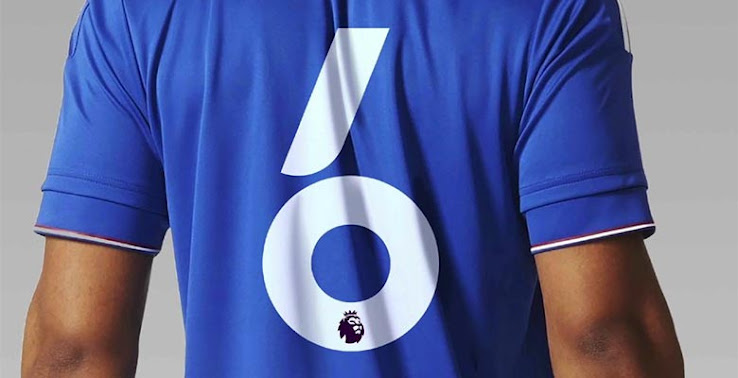
Die neue Premier League Schriftart, die online kursiert, ist echt
Der auf Fußball spezialisierte Twitter-Account @TheModernGame_ hat in dieser Woche ein Bild dessen gepostet, was man selbst als neue Schriftart für die Premier League bezeichnet.
Die vermeintlich neue Premier League Schriftart, die von der optischen Identität inklusive des neu entworfenen Wappens inspiriert wurde, würde eher ungewöhnlich aussehen, was durch ein Symboldbild mit Chelseas Baba Rahman unter Beweis gestellt wird. Glücklicherweise ist es nicht für die nächste Spielzeit, und noch in der Arbeit - aber auf jeden Fall nicht das fertige Produkt.
Tatsächlich wird die Schriftart der Premier League für Spielernamen und -nummern in der nächsten Spielzeit unverändert bleiben, wie wir im Mai enthüllt haben. Dies wurde bereits von der Firma bestätigt, die für das Design zuständig ist, SportingID.
Jedoch IST die Schriftart in einem Gespräch von DesignStudio, dem Studio hinter der neuen Ligaidentität, zur Sprache gekommen. "And we're busy working a shirt name and number typeface for next season." („Und wir sind damit beschäftigt, eine Schriftart für Trikotnamen und -nummern für die nächste Saison auszuklügeln“) (Bei 12 verstrichenen Minuten im Video). Also könnten wir vielleicht etwas in der Art dieser Schriftart ab 2017 erhalten.